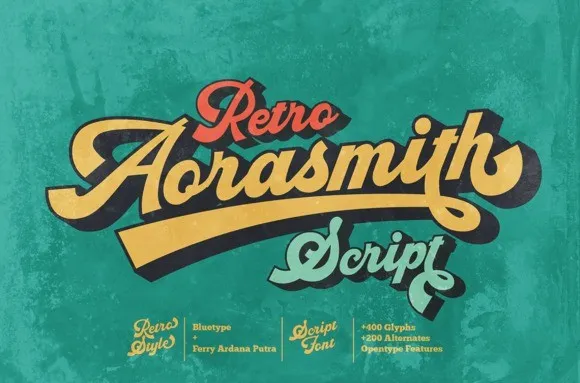
Aorasmith Script Font – Download Grátis
A Aorasmith Script Font é uma elegante e amigável tipografia escrita a mão, ideal para quem busca uma fonte que se destaca em qualquer contexto. Seja ela utilizada em fundos atarefados ou como um título independente em capas de revistas, esta fonte será sua escolha perfeita. Desenvolvida e compartilhada pela bluetype, a Aorasmith é uma tipografia para uso de exibição que vai transformar seu design retro com facilidade. É perfeitamente adequada para ambientes onde você deseja criar um visual arcaico, mas moderno ao mesmo tempo. Seja em suas criações de identidade visual ou em projetos web, a Aorasmith trará uma pegada clássica e contemporânea, deixando seu design pronto para ser destacado.